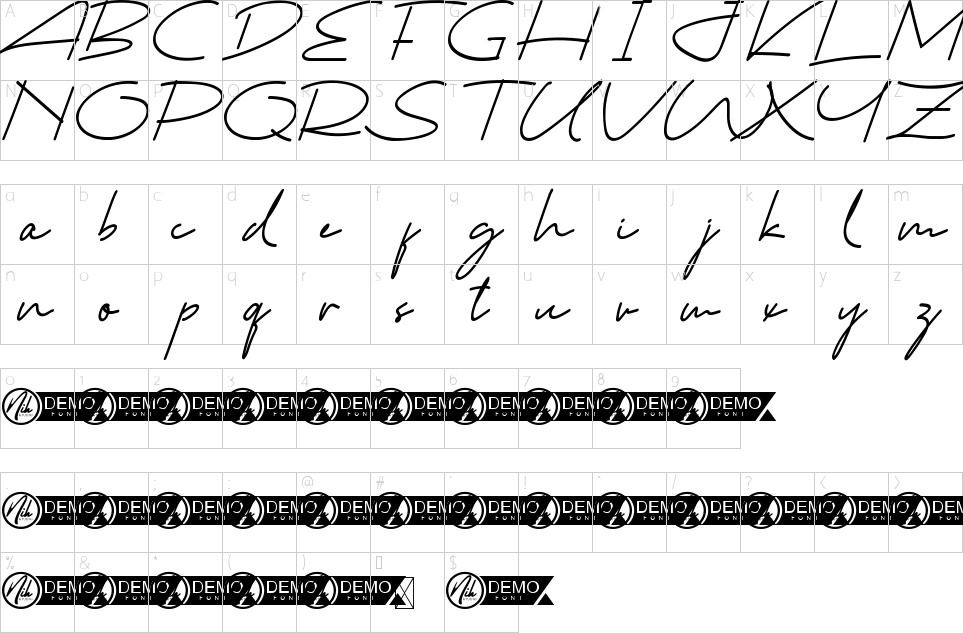
A Go And Back é uma nova fonte grátis que você definitivamente não pode encontrar por aí. Desenvolvida pelo NihStudio, esta fonte foi projetada para aqueles que adoram um estilo leve e fresco na sua escrita digital. Com seu design minimalista e versátil, ela se destaca no universo das fontes gratuitas, oferecendo uma experiência de escrita agradável sem o custo adicional. Esta nova fonte garante uma variedade de opções para seus projetos, seja para o texto de um site ou o design do seu próximo livro digital. A Go And Back é uma excelente opção para quem busca novas maneiras de expressar-se através da tipografia, sem se preocupar com os custos. Descubra por si mesmo como essa fonte pode revolucionar a maneira como você escreve e visualiza o conteúdo digital em seu dia-a-dia.